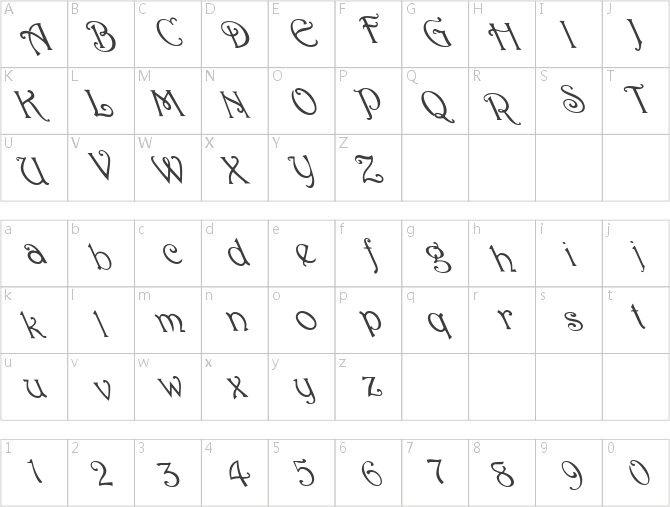
FZ JAZZY 2 LEFTY 詳情頁(yè)
FZ JAZZY 2 LEFTY字體字庫(kù)是一款讓人賞心悅目、百看不厭的英文字體,適合各類廣告和產(chǎn)品包裝設(shè)計(jì)應(yīng)用,字體大小0.05MB,格式為ttf字體,上傳用戶是眾聯(lián)齊成,作者/版權(quán)方為未知